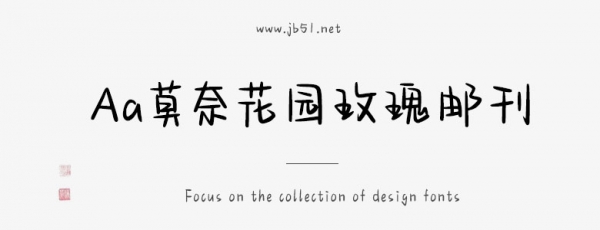
Aa莫奈花園玫瑰郵刊由Aa字庫(kù)出品的藝術(shù)字體,字體筆觸纖細(xì),書(shū)寫(xiě)流暢灑脫,適合應(yīng)用于藝術(shù)設(shè)計(jì)、平面宣傳設(shè)計(jì)、網(wǎng)頁(yè)設(shè)計(jì),書(shū)法字帖等領(lǐng)域。有需要的朋友快來(lái)本站下載使用吧。